Как оценить наклон и насыщенность курсивной гарнитуры
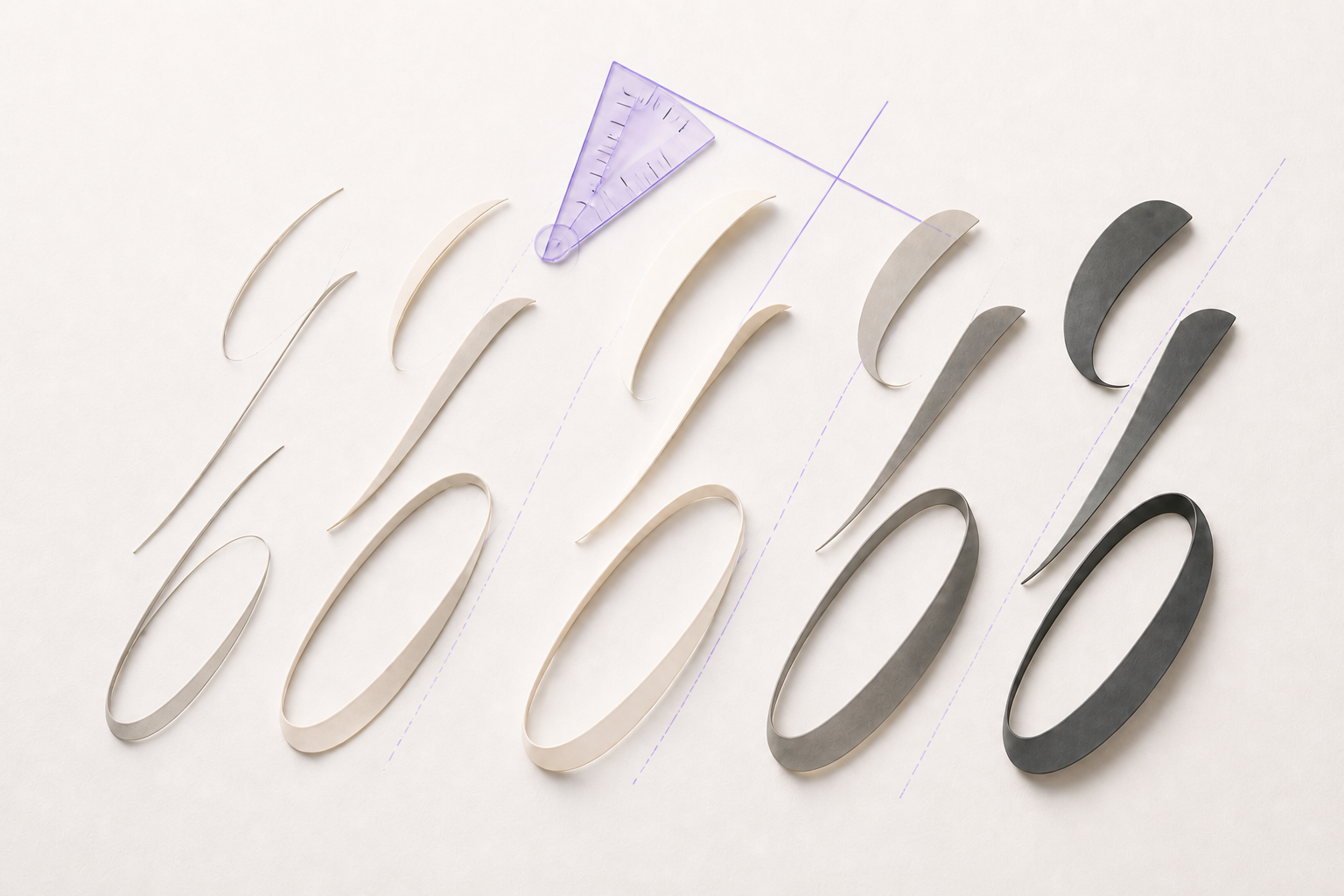
Как оценить наклон и насыщенность курсивной гарнитуры
Оценивать наклон и насыщенность курсивной гарнитуры нужно не по одному параметру, а по тому, как шрифт ведёт себя в словах, строках и разных кеглях. Сначала сравните угол и ритм штрихов, затем проверьте вес, контраст, просветы, читаемость и соответствие задаче — от интерфейса до акцидентного заголовка.
Материал актуален на 27 августа 2026 года. Он поможет отличить выразительный, хорошо сбалансированный курсив от механически наклонённого начертания, которое выглядит тяжёлым, рыхлым или плохо читается.
Почему одной цифры угла недостаточно
Наклон шрифта воспринимается как движение строки, но его нельзя оценить только по геометрическому углу. Два начертания могут иметь похожее положение букв, однако одно будет выглядеть энергичным и лёгким, а другое — неуклюжим. На впечатление влияют форма овалов, ширина знаков, длина выносных элементов, межбуквенные просветы и чередование вертикальных и наклонных штрихов.
Насыщенность также не равна простому количеству чёрного цвета. Важны толщина основных и соединительных штрихов, контраст, размер внутренних просветов, форма засечек и то, как буквы распределяют плотность по строке. Поэтому начертание с меньшим формальным весом иногда кажется темнее более жирного варианта, если у него теснее набор или меньше апертуры.
Что означают наклон, курсив и насыщенность
Геометрический наклон и настоящий курсив
Наклонное начертание часто получают сдвигом вертикальных букв вправо. Это механический подход: форма знаков почти не меняется, меняется только их положение. Настоящий курсив проектируют отдельно. В нём могут измениться пропорции, соединения, окончания штрихов и отдельные буквы. Такой курсив обычно лучше передаёт рукописный характер и сохраняет естественный ритм.
Насыщенность, вес и контраст штрихов
Насыщенность описывает визуальный вес начертания: от тонкого до жирного. При сравнении смотрите не только на толщину вертикалей, но и на тонкие соединительные линии, внутренние пространства и контраст между элементами. Хорошо настроенный курсив сохраняет узнаваемость букв при изменении веса и не превращает тесные формы, например кириллические «ж», «м» или «щ», в тёмные пятна.
Подготовьте корректное сравнение
Оценивайте гарнитуру в условиях, близких к будущему применению. Один и тот же шрифт по-разному выглядит в крупном логотипе, интерфейсной кнопке, подписи к изображению и длинном абзаце. Используйте одинаковый текст, одинаковый размер, одинаковую длину строки и одинаковый цвет. Иначе вы будете сравнивать не шрифты, а разные настройки набора.
- Возьмите нейтральную фразу с буквами разной формы, цифрами и знаками препинания.
- Добавьте кириллические пары «д—л», «т—ш», «к—ж» и буквы с выносными элементами.
- Проверьте отдельные слова, короткие строки и связный абзац.
- Сравните начертания в нескольких кеглях, а не только в одном крупном размере.
- Используйте одинаковые межбуквенные интервалы и межстрочное расстояние.
- Посмотрите на образец сначала в масштабе, а затем в уменьшенном виде.
Пошаговая оценка курсивной гарнитуры
1. Определите характер движения
Сначала оцените строку целиком. Курсив должен создавать направленное движение, но не выглядеть так, будто буквы падают вправо. Слишком слабый наклон может почти не отличаться от обычного начертания, а чрезмерный нарушает устойчивость строки. Смотрите, сохраняются ли одинаковый темп, базовая линия и визуальный центр слов.
2. Сравните вертикали и овалы
В строчных буквах проверьте, насколько согласованно наклонены основные штрихи и овальные формы. Если одни элементы уходят вправо заметно сильнее других, ритм становится рваным. В хорошей гарнитуре наклон поддерживает форму: овалы не выглядят сжатыми случайным образом, а соседние буквы не сталкиваются своими верхними и нижними элементами.
3. Проверьте вес в реальном наборе
Наберите фразу обычным и курсивным начертанием одного семейства. Курсив не обязан иметь идентичную плотность с прямым начертанием, но разница должна быть осмысленной. Если курсив заметно темнее, он начнёт перетягивать внимание. Если светлее, потеряется в подписи или ссылке. Сравнивайте не одну букву, а несколько строк: только так видны накопленные различия.
4. Изучите внутренние просветы
Внутренние просветы определяют, насколько легко различать знаки. В курсиве особенно важны пространства внутри «а», «е», «о», «с», а также открытые формы «в», «з» и «э». При высокой насыщенности они не должны закрываться. Если буквы сливаются в слова-«комки», проблема может быть не в самом весе, а в сочетании веса, ширины и межбуквенного расстояния.
5. Проверьте кириллицу и специальные знаки
Кириллический курсив нельзя оценивать только по латинским образцам. У букв могут меняться форма, наклон, соединения и пропорции, а привычные для латиницы решения не всегда работают в русском тексте. Проверьте прописные и строчные знаки, кавычки, тире, проценты, валютные символы, цифры и диакритические знаки, если они нужны проекту.
Оценка курсива — это проверка не отдельного угла и не формальной толщины, а согласованности всего набора. Сравнивайте наклон, ритм, вес, контраст, просветы и кириллические формы в реальном сценарии. Так вы поймёте, подходит ли гарнитура для интерфейса, текста, брендинга или крупной типографики.